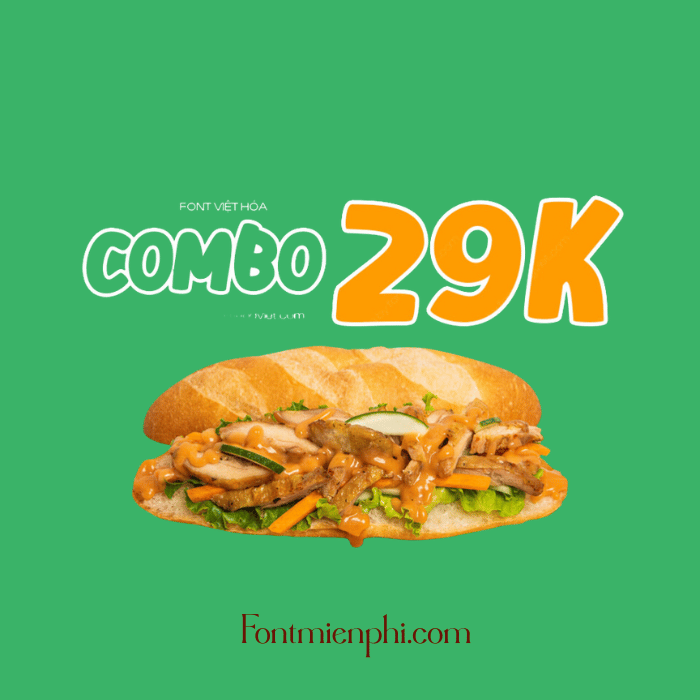
Font Việt hóa 1FTV VIP Vanily – Phong Cách Độc Đáo, Thiết Kế Chuyên Nghiệp
Font 1FTV VIP Vanily là bộ font Việt hóa cao cấp, được thiết kế tinh tế với nét chữ mềm mại, sang trọng, phù hợp cho các dự án sáng tạo như thiết kế đồ họa, logo, banner, hoặc in ấn. Với bảng mã Unicode đầy đủ, font hỗ trợ tiếng Việt hoàn hảo, đảm bảo hiển thị sắc nét trên mọi nền tảng.
✔ Thiết kế độc quyền – Nét chữ tinh xảo, phong cách hiện đại.
Font Việt hóa 1FTV VIP Vanily là font chữ Việt hóa cho các thiết kế ẩm thực. Với font chữ tiếng Việt Vanily sẽ giúp thiết kế của bạn đẹp hơn, sang trọng hơn. Font Vanily có nét đậm, dày, bo tròn rất dễ thương nhé.